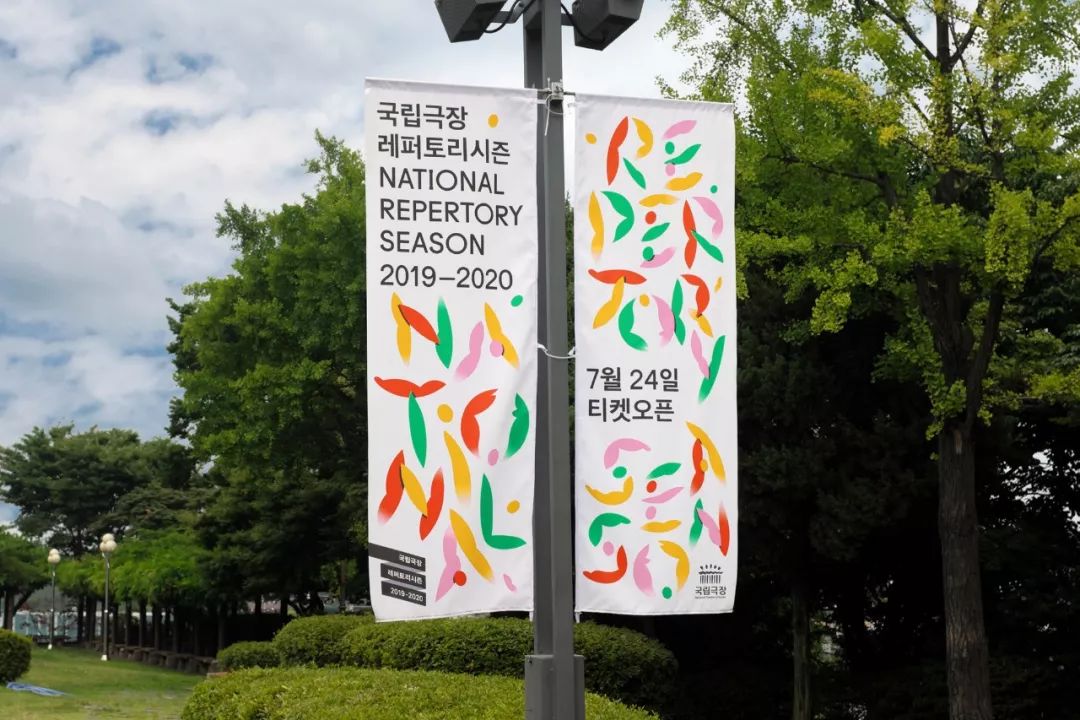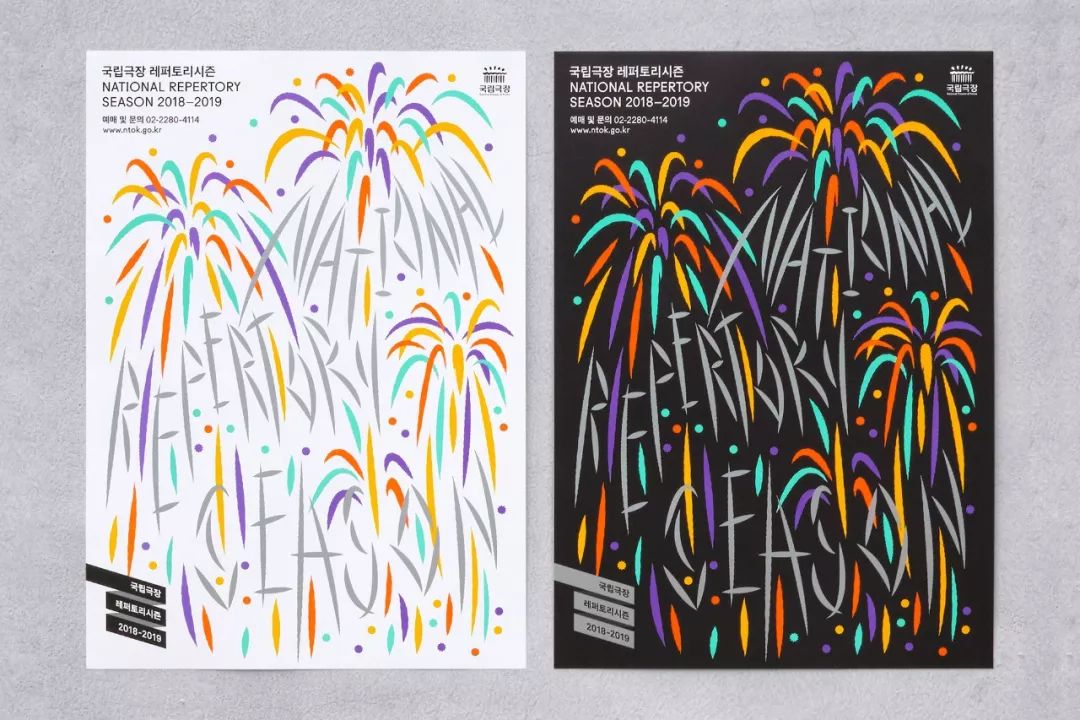
韩国的平面设计怎么样,看这5家工作室就知道
提到亚洲设计,人们总是会先想到日本的设计,日本设计师喜欢用简约、干净的视觉语言来进行表达,而同样是我们邻国的韩国,在平面设计领域的成就同样不容小觑。韩国平面设计的风格大多有着大胆独特的排版样式,其细腻又令人惊艳的色彩运用令人过目不忘。
韩国的设计力量在亚洲已奠定了独树一帜的地位,今天我们将为大家介绍5家年轻的韩国设计工作室,他们大多是位于首尔,设计领域横跨书籍设计、海报设计、网站设计和展览设计等。通过了解他们的作品,学习到更多新颖的视觉表达的方式。
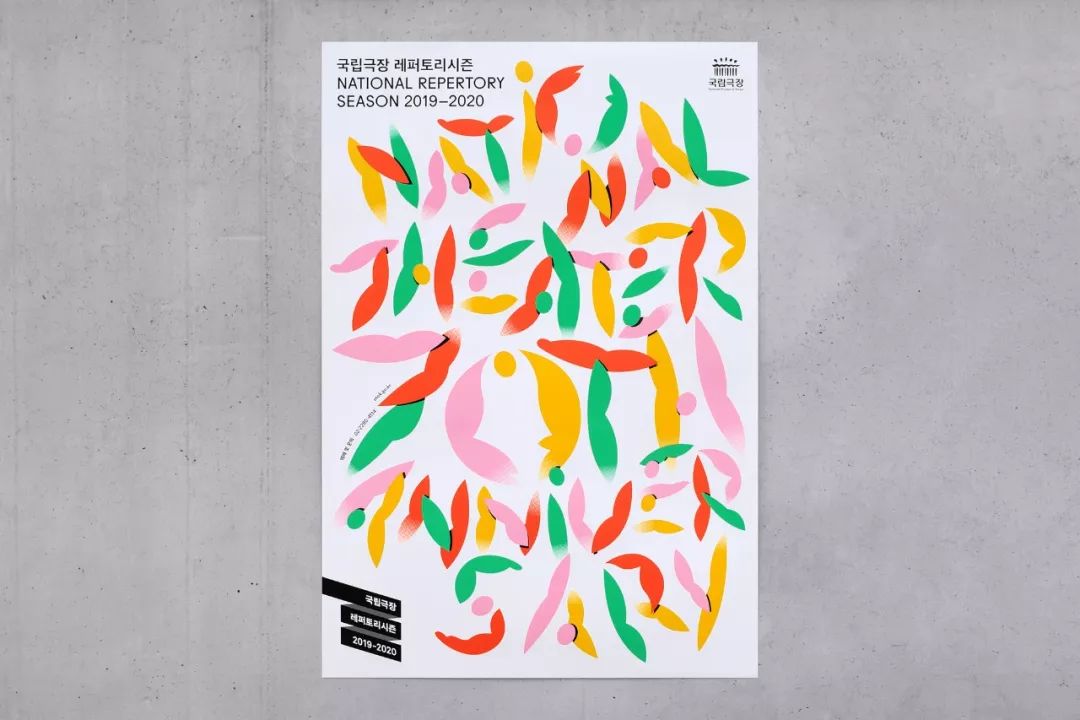
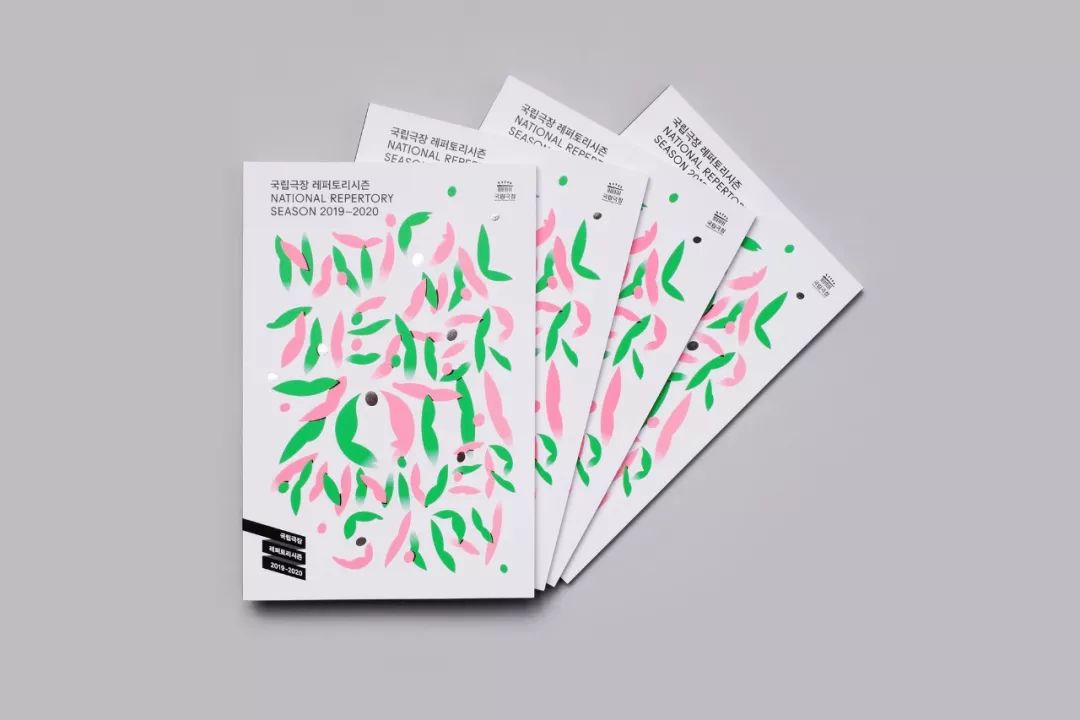
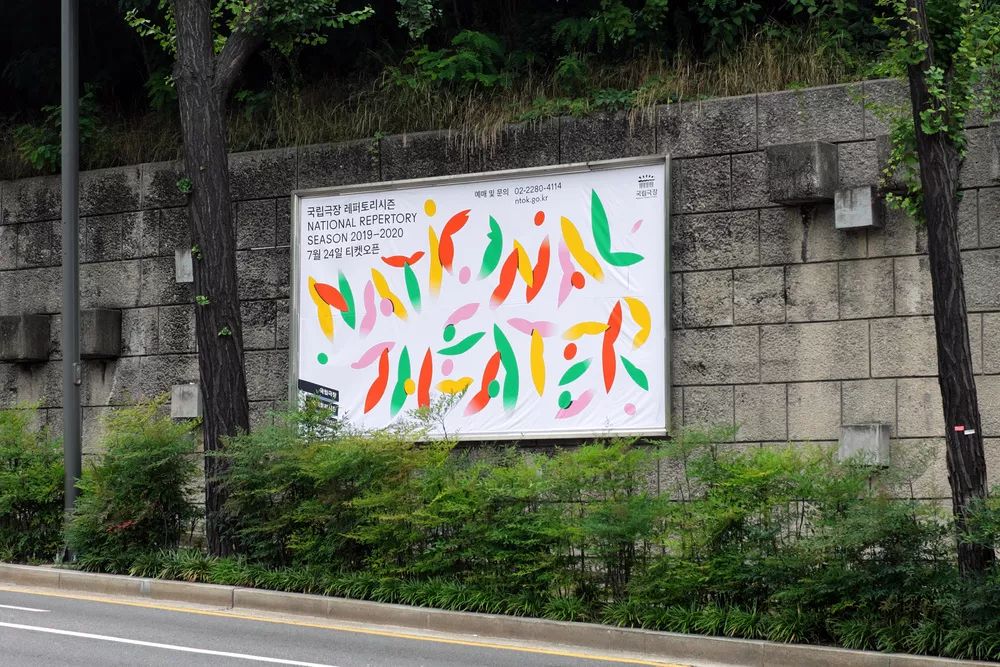
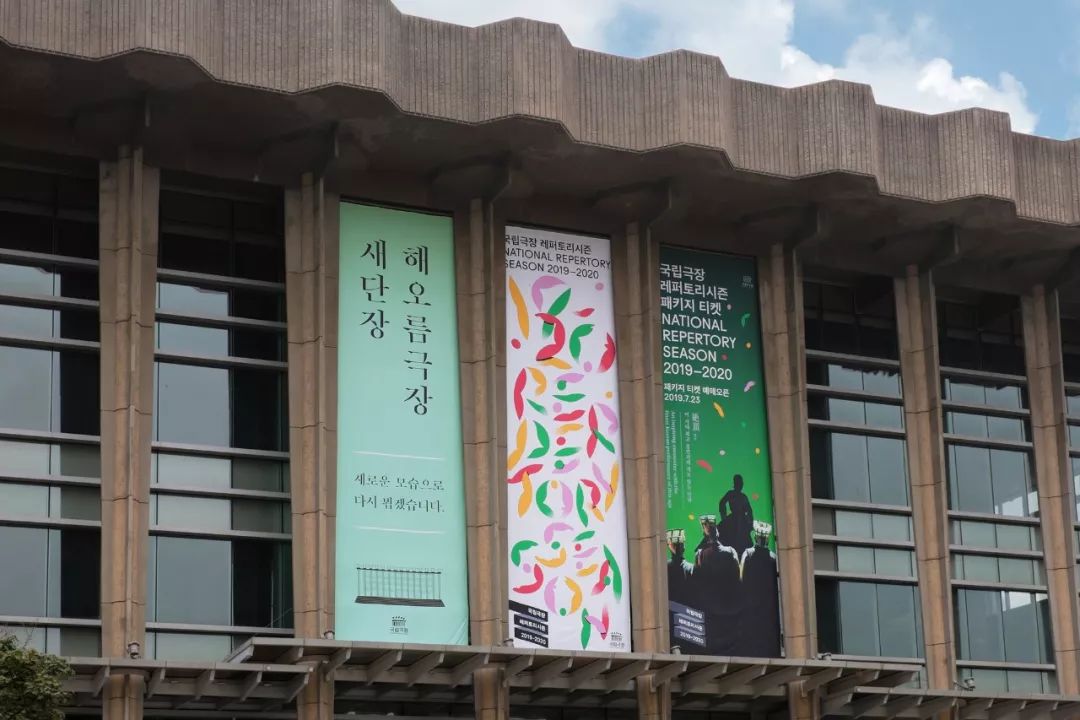01
studio Fnt
Studio Fnt成立于2006年,是一家来自韩国首尔的平面设计工作室,创始人是我们之前介绍过的Jaemin Lee,工作室专注于海报设计、书籍设计、品牌识别、数字媒体和其他领域。Studio Fnt通过有趣的排版、图形元素的组合再融汇各式各样的形状和颜色,呈现出一件件独具创意的作品。Studio Fnt最令人印象深刻的便是活动海报的设计,每一张都有着自己独特的风格。
2019-2020年
韩国国家大剧院剧目季
韩国国家大剧院成立于1950年,70年来一直是韩国艺术表演的先驱。“国家剧目季”是一个韩国的年度节目,展示国家艺术团体在戏剧、传统戏剧、舞蹈和管弦乐队方面的创新作品和最佳剧目。
2019-2020年韩国剧目季的视觉概念是“舞蹈”。Studio Fnt的灵感来自于知名艺术家亨利·马蒂斯作品中的节奏形式,大胆、丰富的色彩为画面带来了活力。它们就像花和叶的形状,或者像强有力的身体运动的表现,这些图形在纸上自由地聚集和分散,形成了字体。
2018-2019年
韩国国家大剧院剧目季
2018年第16届威尼斯建筑双年展
韩国馆主视觉设计
韩国国立现代美术馆
视觉识别
02
Jin & Park
Jin & Park 是一个双人艺术家、设计师组合,由JIN dallae & PARK woohyuk两位设计师组成。他们热衷于研究、探讨可见与不可见、内在与外在、起始与终点之间的灰色地带。他们举办过多场个展,曾参与韩国国立现代美术馆展览Unforeseen,并于2015 年双双入选国际平面设计联盟成员。作品横跨印刷设计、装置、表演和音频体验。
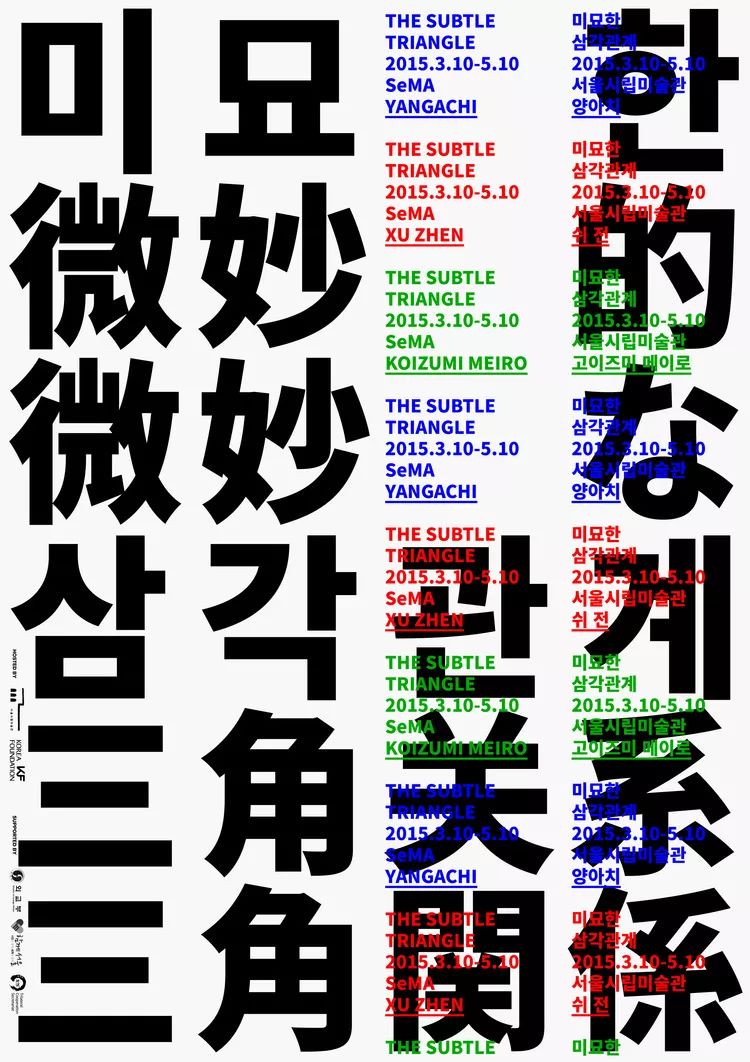
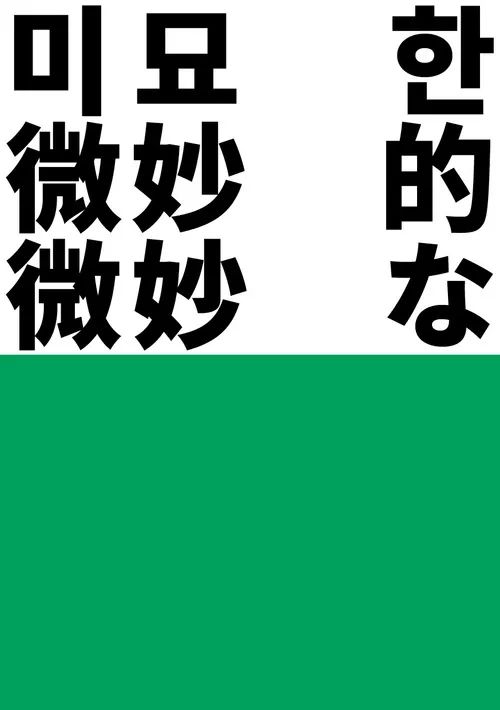
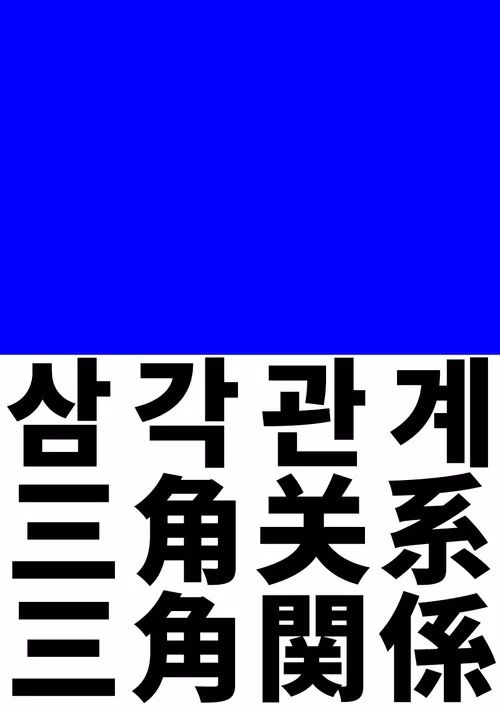微妙的三角关系
2015首尔艺术博物馆展览主视觉
2017韩国国立现代美术馆主视觉
完美的A
海报设计
2018光州艺术艺术节
海报设计
2017金浦艺术库海报设计
2016白南准艺术中心
展览海报设计
2016布鲁塞尔韩国文化中心
展览海报设计
03
Ordinary People
2006年,当时还是平面设计专业学生的Jin Kang和几个朋友开始了一个名为“我们做海报(We Make Posters)”的项目,随着项目进展的逐渐深入,最终演变为一个平面设计工作室。以约翰·传奇(John Legend)的歌——《普通人》作为工作室的名字。Ordinary People涉及的范畴跨越多个学科,其中包括展览视觉、视觉识别、专辑封面设计等等,同样的,他们的海报设计作品也令人印象深刻。
2018公共设计展:人人享有的美好空间
视觉识别
2018公共设计展:人人享有的美好空间,是为宣传2018公共设计大奖得主而举办的展览。Ordinary People的目标是通过公共设计,利用城市街道的几何形状、有节奏的线条和活泼的色彩,将普通的景观改造成适合所有社会公民享用的空间。
2017SIFF首尔独立电影节
视觉识别
Ordinary People选择了一系列的画面来表达电影节的视觉。每一帧都代表着过去、现在和未来。帧序列在“MADE IN NOW”处改变方向。通过这个,“此时此刻”在无数的时刻被注意到。
2018首尔独立电影节
海报设计
韩国潇洒园:一个神秘的长廊
海报设计
ubies画廊商店快闪店
海报设计
2018CKL舞台海报设计
04
Kim garden
Kim garden是由韩国平面设计师Yunho Lee 和 Kangin Kim共同创立的平面设计工作室,从品牌识别到网页设计,从书籍设计、海报设计到展览设计,无所不包。Kim garden的设计干净利落,但充满了疯狂、古怪的细节。
2019 Peppertone俱乐部巡演
全州国际电影节
影片《鹭梁大捷》海报设计
《带我回家》
视觉识别
单曲《恋曲》
海报设计
全州国际电影节
影片Swagger海报设计
2017亚洲文化中心ACC学院
视觉识别
Quantum Jump艺术展
海报设计
全州国际电影节
影片《港町》海报设计
午夜首尔,乐天世界塔
视觉识别
唱片废墟9
地下唱片市场海报设计
声音工作室现场
海报设计
Marginal
唱片设计
05
Everyday Practice
Everyday Practice工作室的创始人认为,在今天,平面设计的输出越来越相似,因为每个人都可以使用Illustrator和Photoshop等设计工具来进行创作,而他们更喜欢基于工艺的原理来进行创作,这可以使得作品的色彩与众不同。
韩国河南二聖山城文化节
海报设计
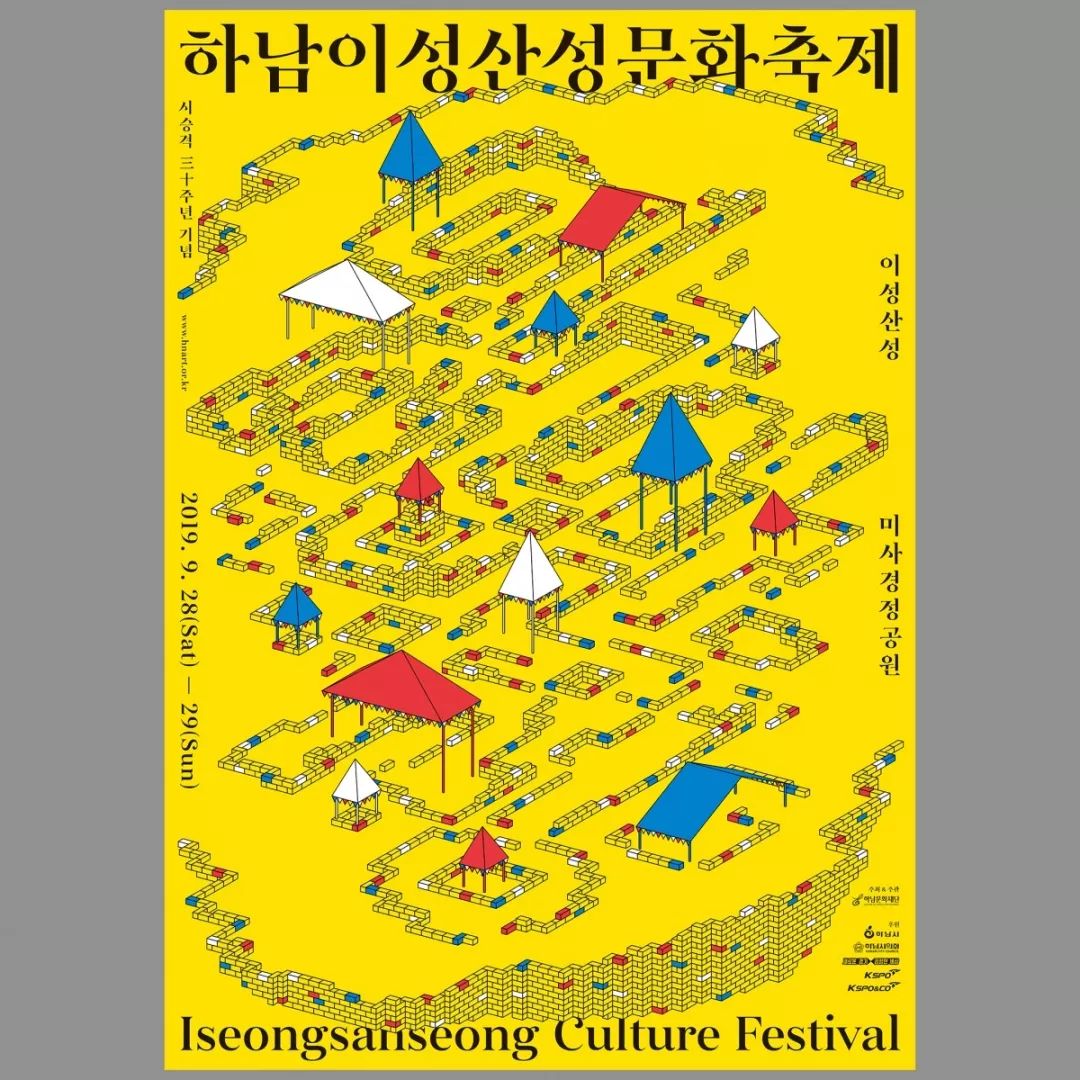
Yeowoorak 音乐节
海报设计
2019首尔插画展
视觉识别
Hello! Sem
海报设计